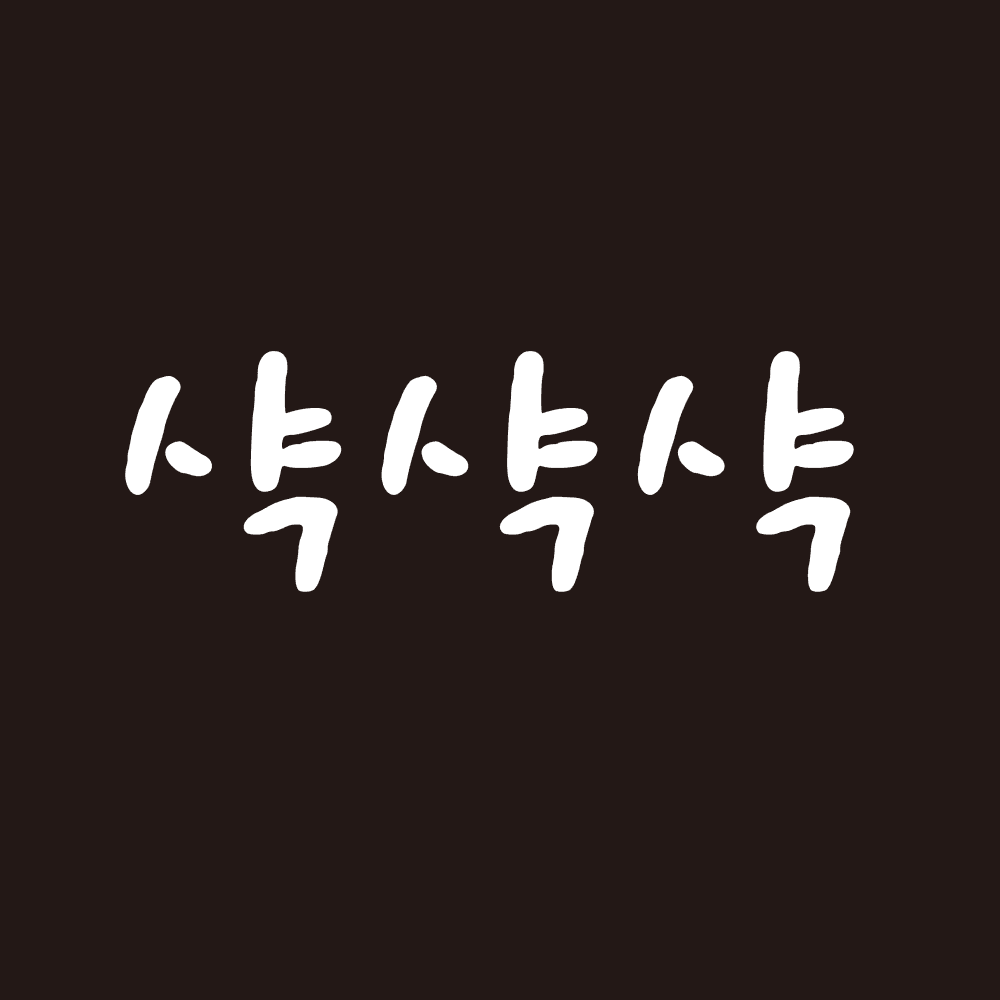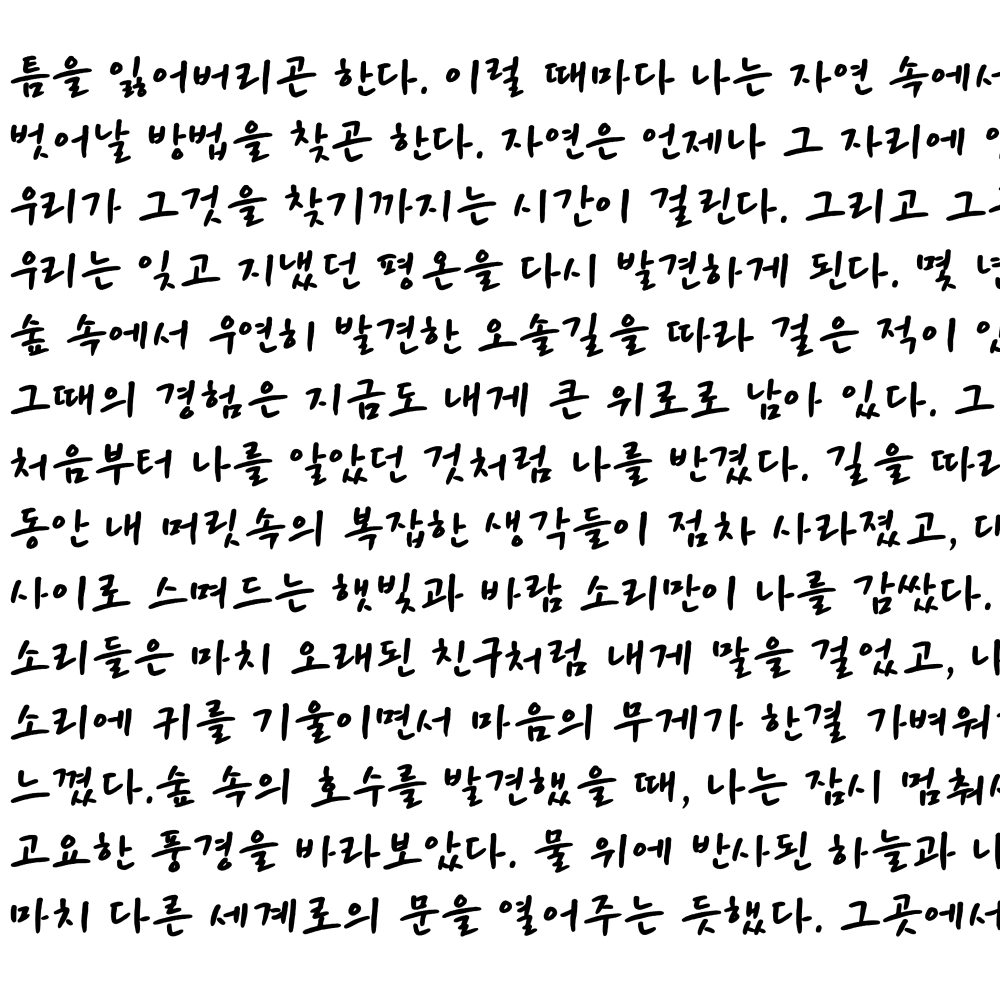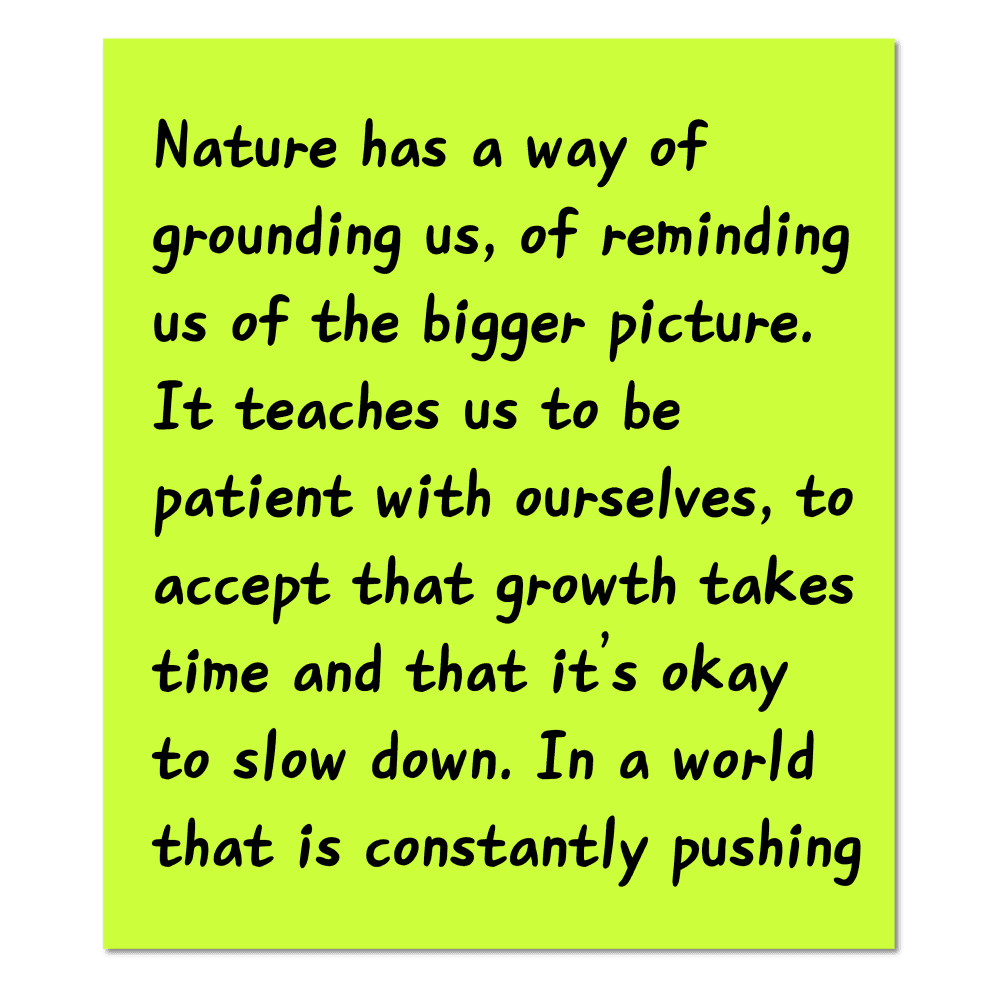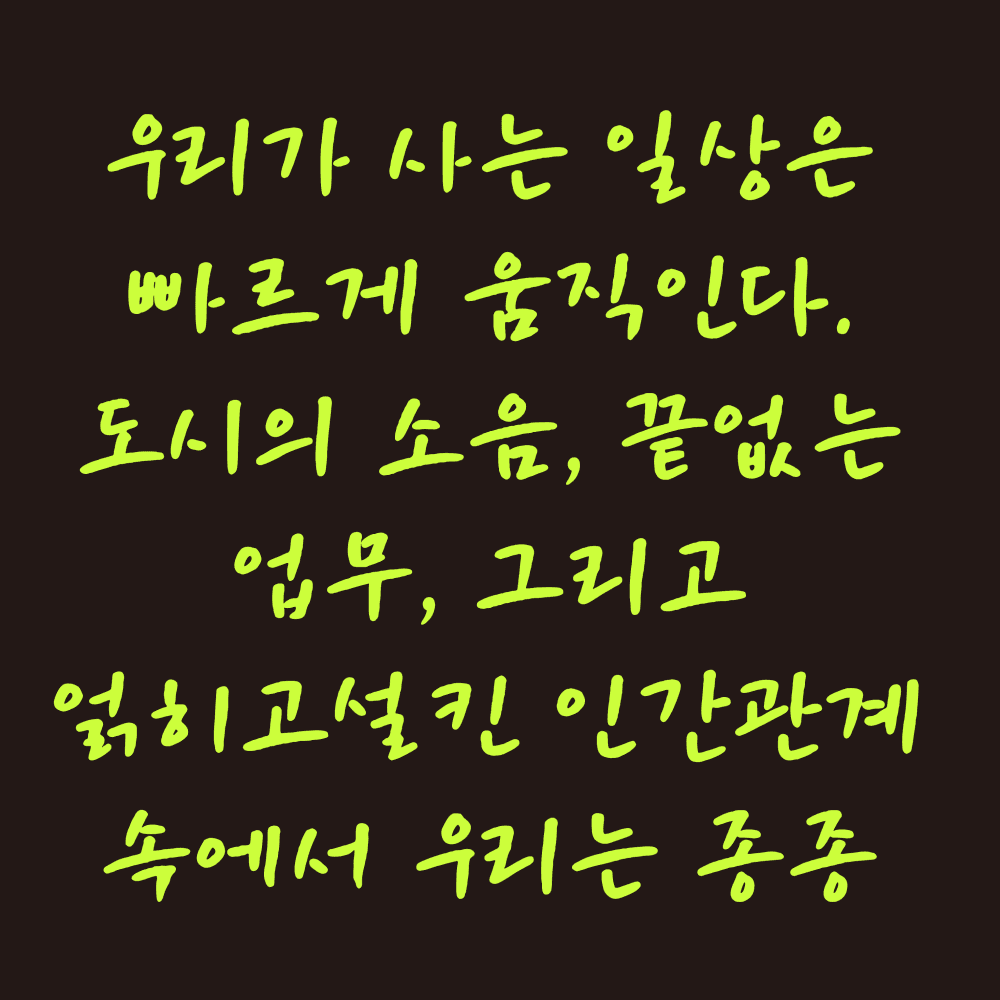
그리운 샥샥샥
Griun Shakshakshak
한글 11,172자
특수기호 33자
그리운 샥샥샥 소개
그리운 샥샥샥 폰트는 손글씨 느낌을 잘 살린 감성적인 디자인이 특징입니다. 네임펜으로 속도감있게 써내려가는 느낌을 담아내었고, 이름도 글자를 쓰면서 나는 소리 '샥샥샥' 으로 지었습니다. 자유롭고 자연스러운 분위기를 자아내며 부드럽고 경쾌해 친근한 인상을 줍니다. 아날로그적인 느낌을 살리고 싶을 때나 일기장, 메모, 포스터 등에서 따뜻하고 친근한 분위기를 연출하는 데 적합합니다. 글자의 간격이나 형태가 정형화되지 않은 자연스러움이 매력 포인트이며, 필기감이 느껴지는 디자인으로 과거의 추억을 불러일으키는 데 탁월한 폰트입니다.